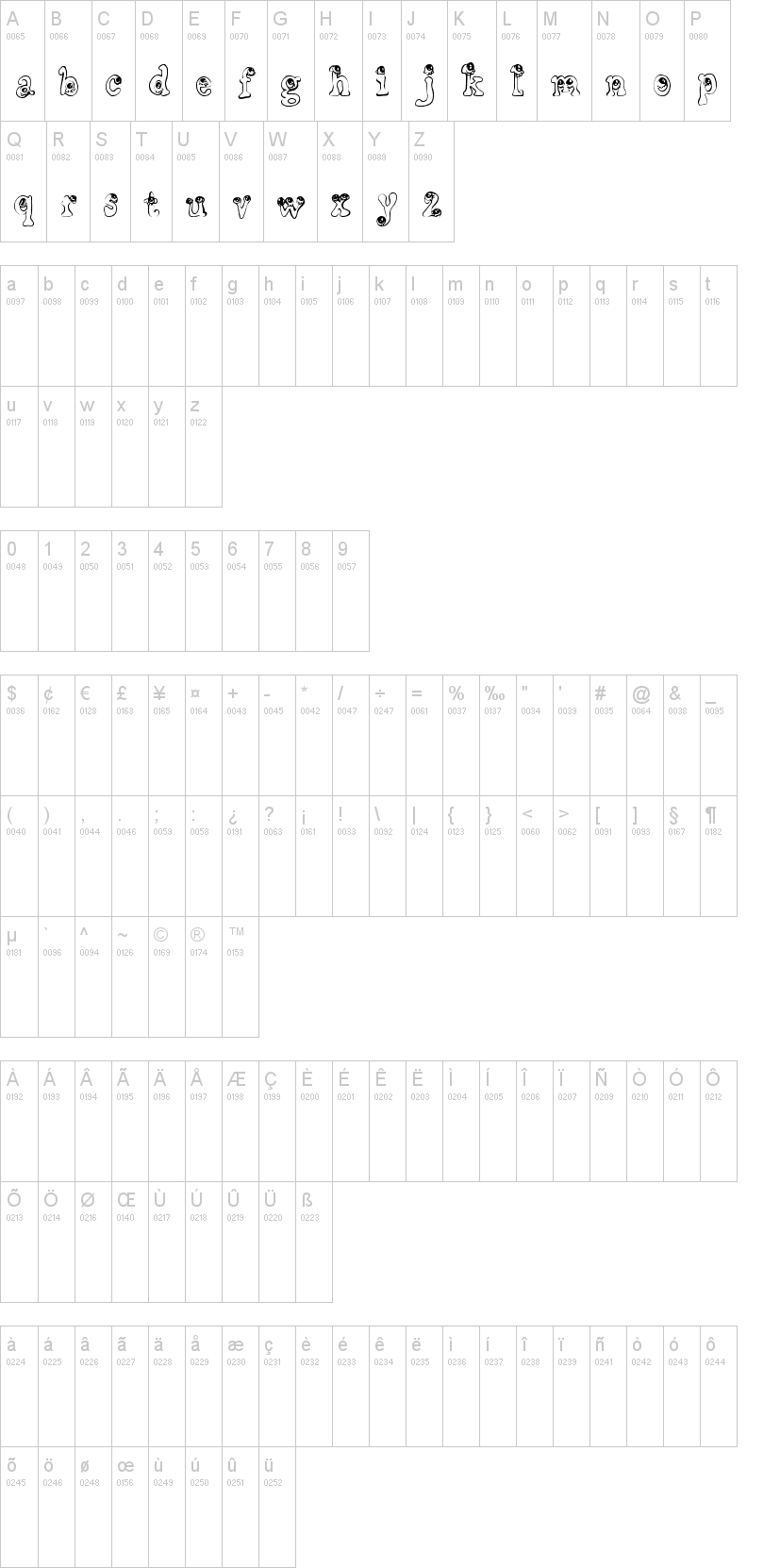
CF Little Monsters 是一款免费的手写风格字体,适用于各种设计项目,特别是与儿童有关的设计。这款字体的设计灵感来自于孩子们手写的字体,具有活泼、有趣和俏皮的气息。它的每个字母都有自己独特的特点,包括一些小怪物的图像,这使得这款字体非常适合用于制作儿童书籍、海报、广告和其他儿童相关的设计。此外,CF Little Monsters 字体也可以添加到您的博客、网站和社交媒体的设计中,以增加视觉上的吸引力。内容介绍
CF Little Monsters是一款非常不错的手写艺术字体,具有很好的视觉感,适合于文化类的宣传设计、商业类品牌的广告和产品包装设计以及个性化文字排版等较多场景。